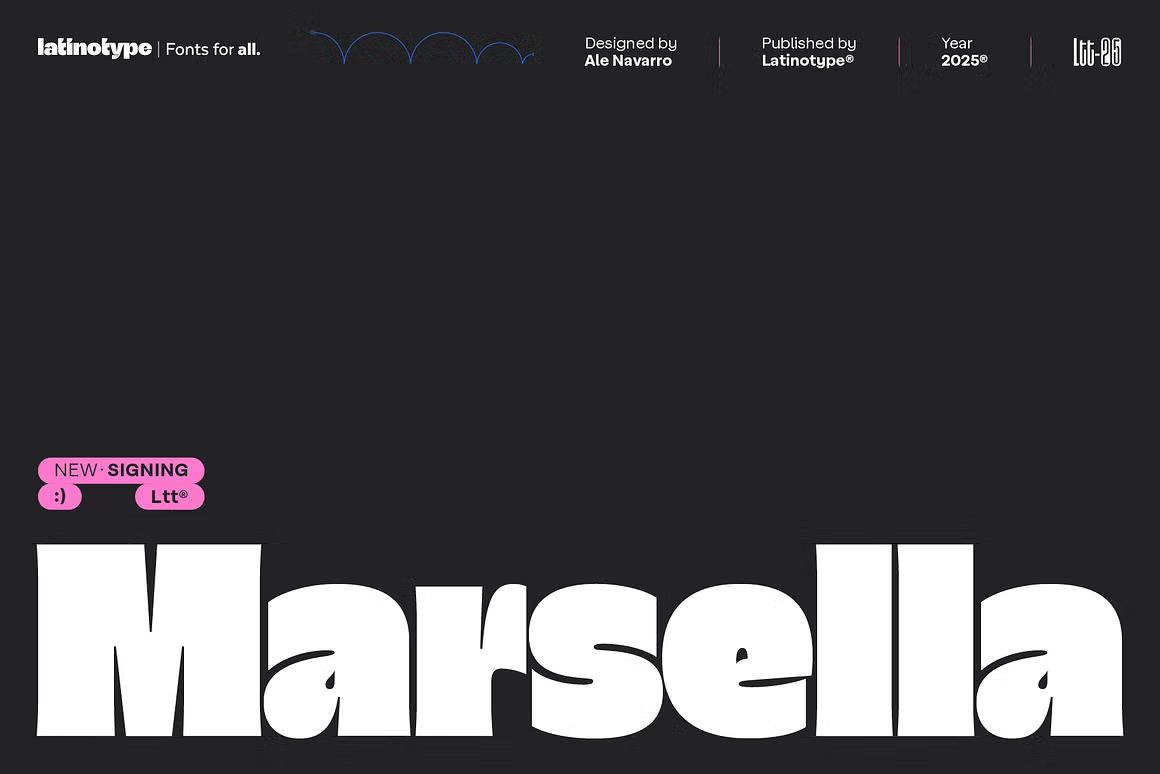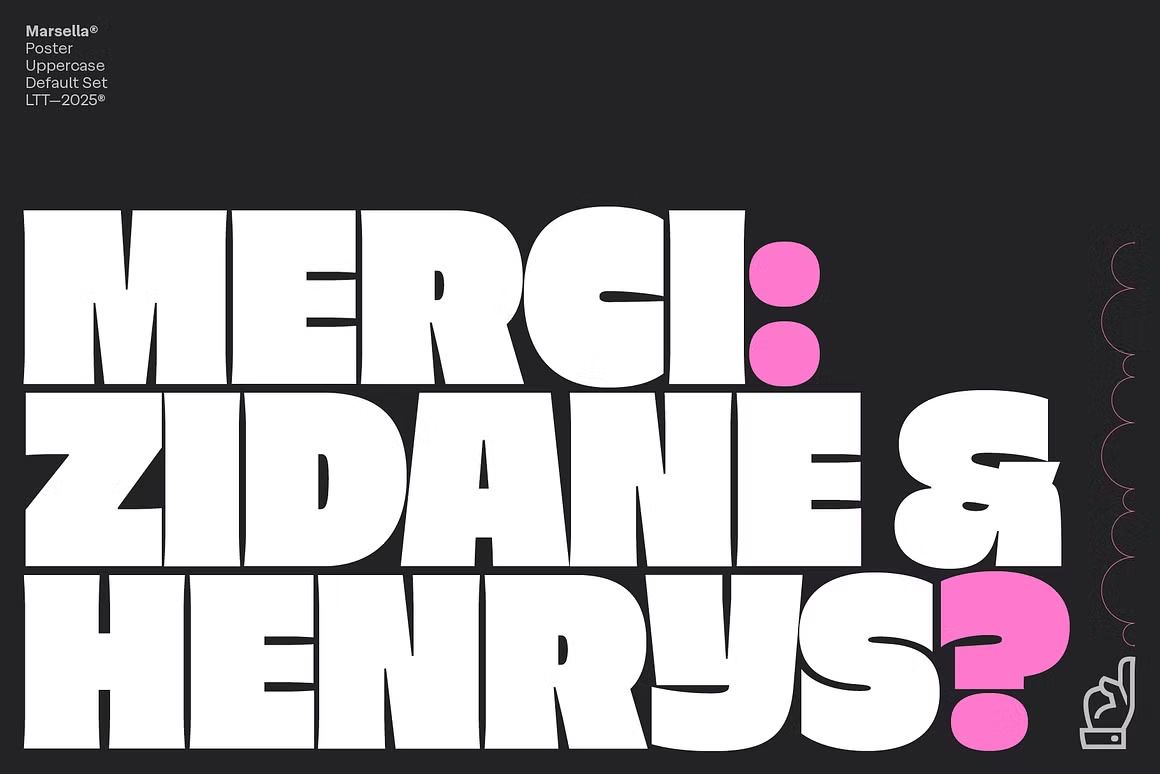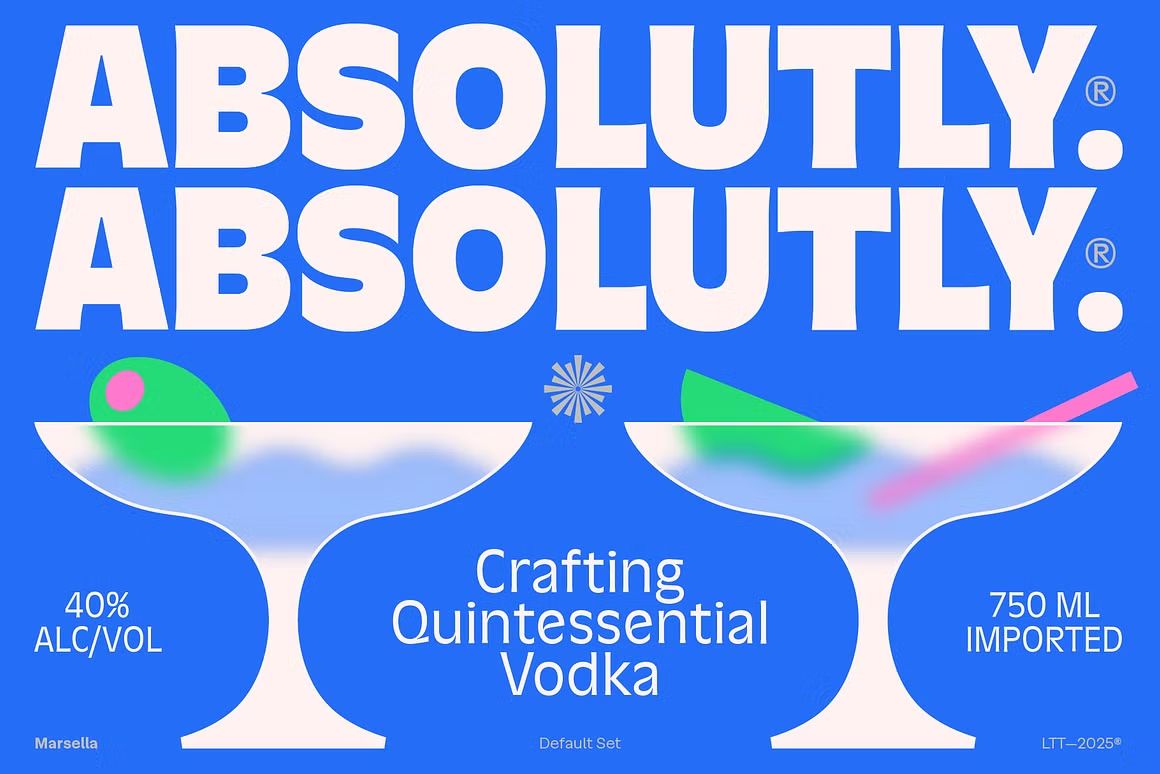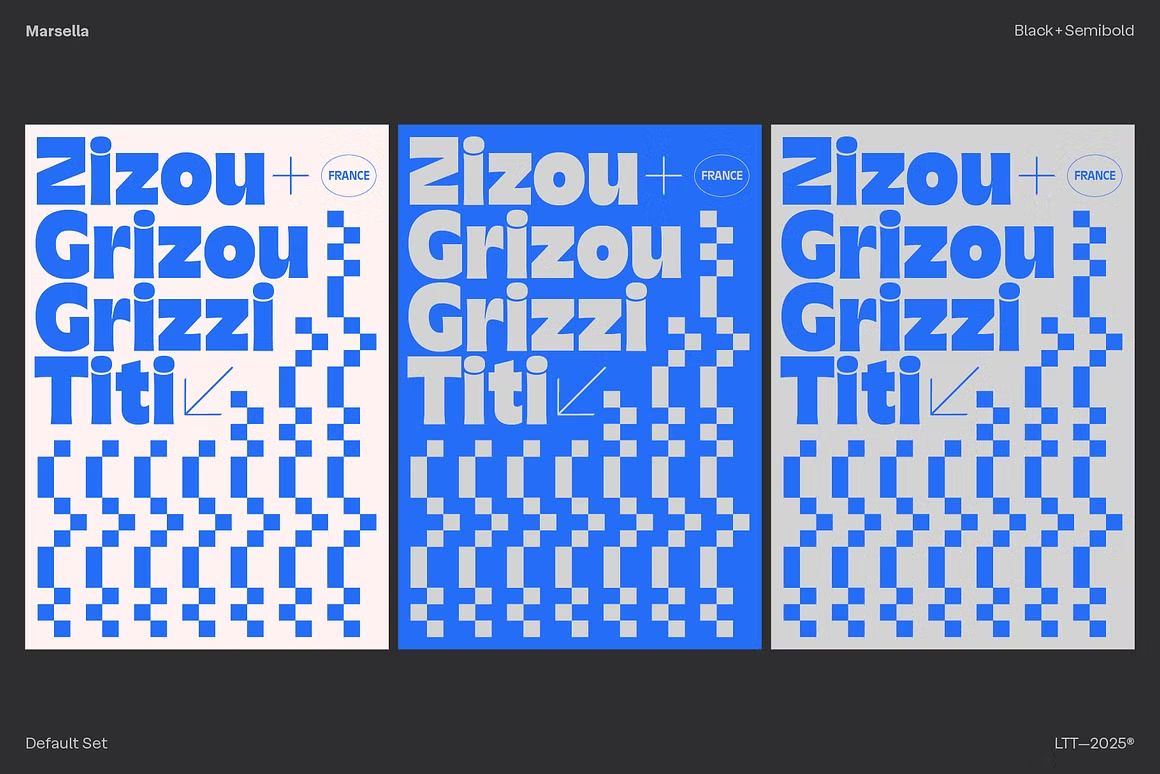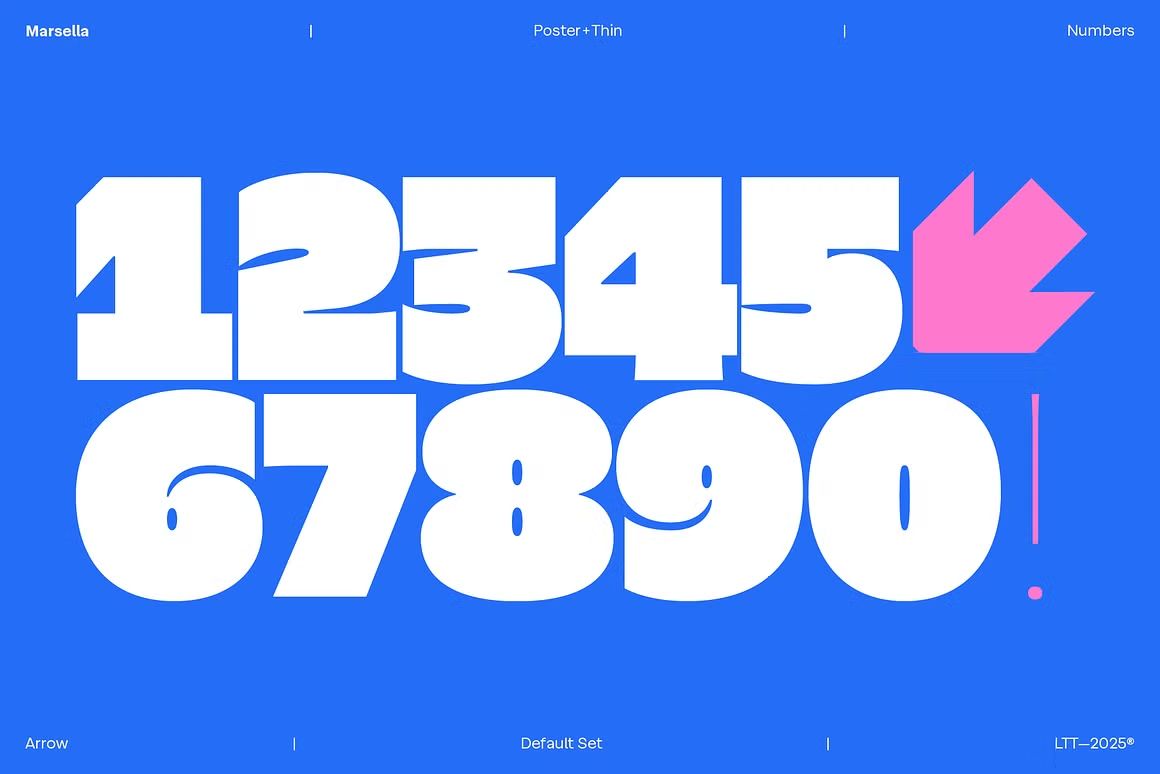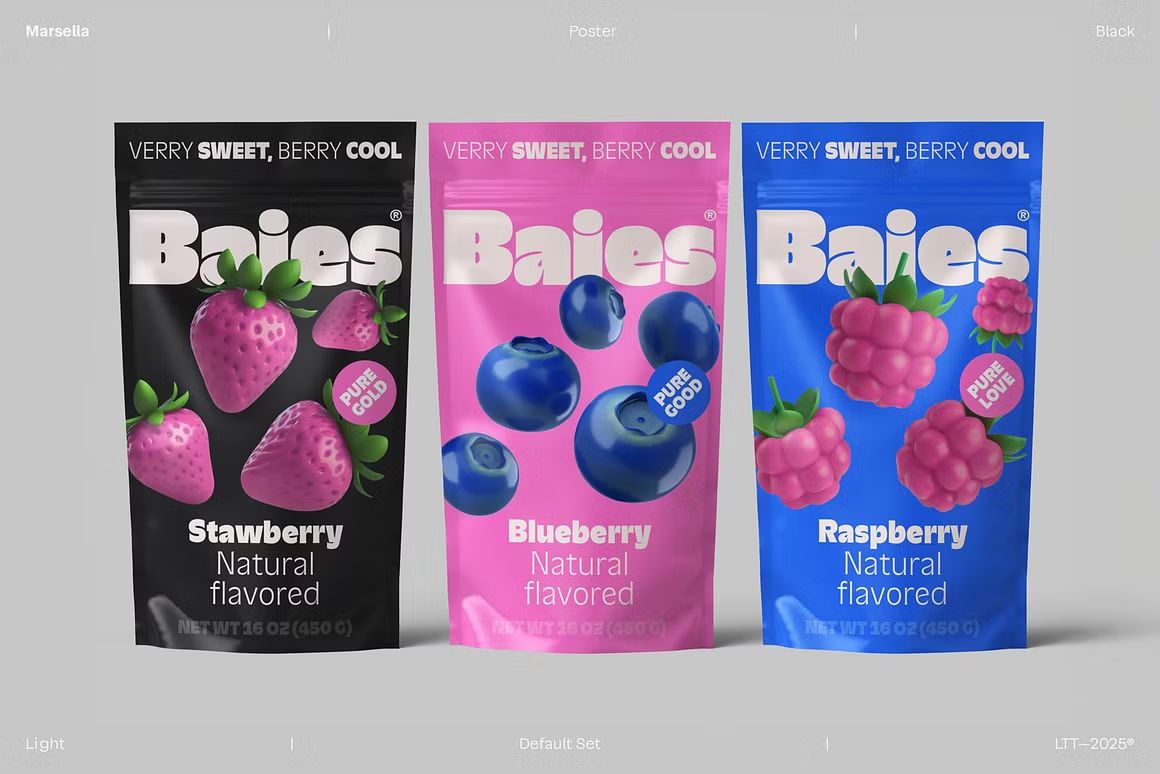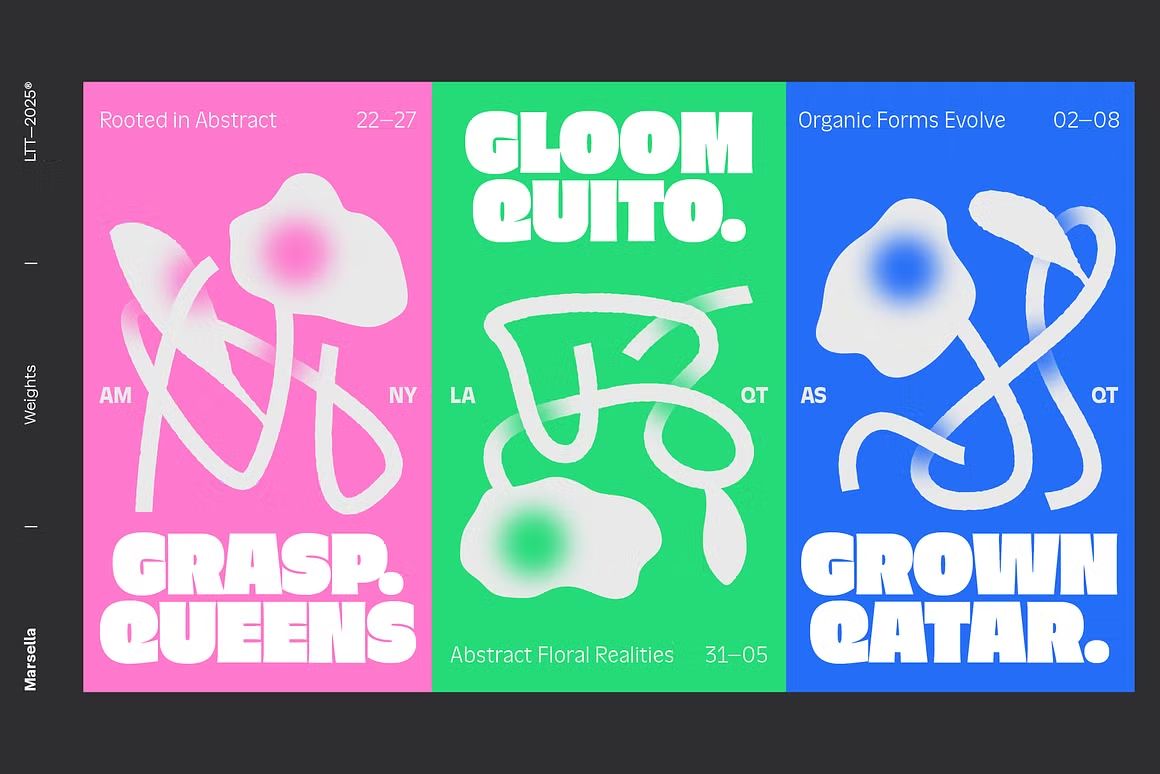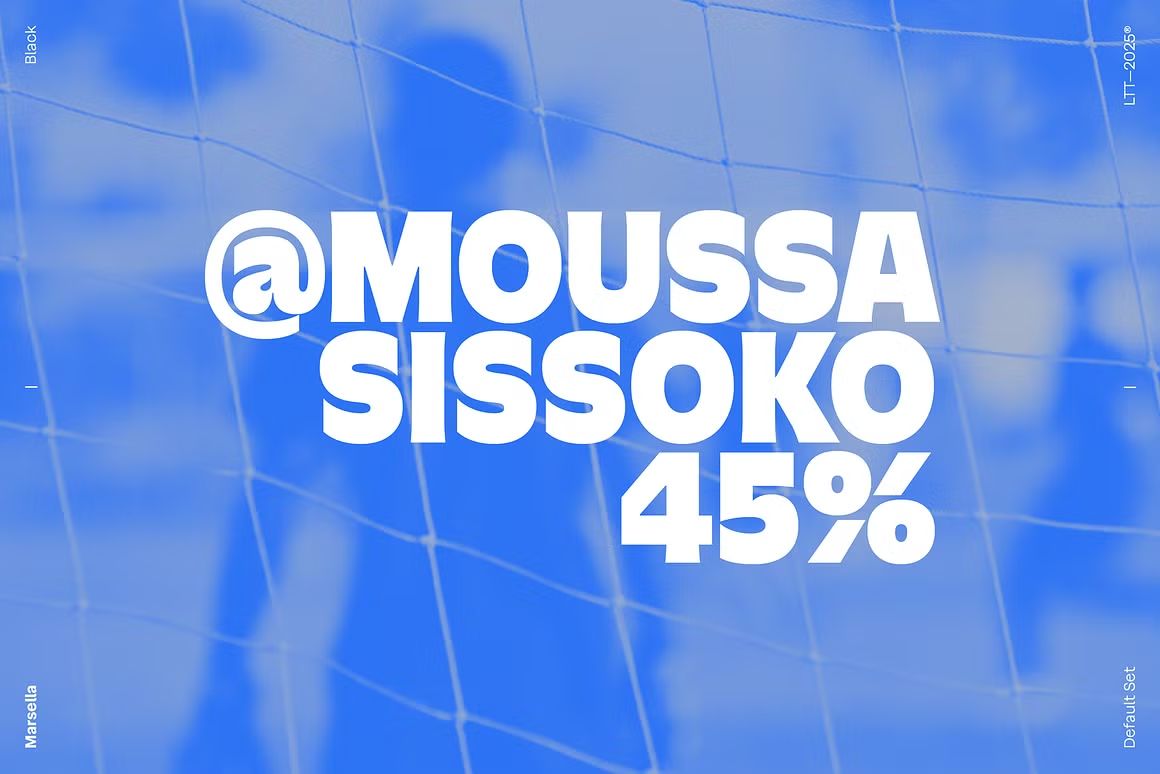
Marsella – Sans Serif Font
Marsella adalah font sans serif modern dengan sentuhan elegan dan profesional. Menampilkan bentuk huruf yang bersih, proporsional, dan mudah dibaca, font ini cocok untuk branding, editorial, desain fashion, kemasan produk, dan presentasi bisnis. Kombinasi antara kesederhanaan dan keanggunan membuat Marsella ideal untuk berbagai gaya visual yang membutuhkan tampilan premium.
• Sans serif modern dengan kesan elegan dan bersih
• Cocok untuk branding, editorial, dan desain fashion
• Termasuk huruf kapital, kecil, angka, dan simbol